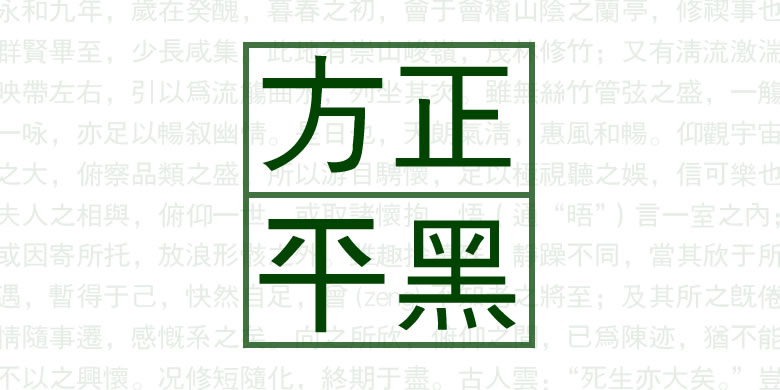
方正平黑
品牌:方正字库设计师:方正字模部发行时间:1996字库编码:大陆繁体(GB12345-90)、港台地区(BIG-5)分类:黑体
方正平黑
方正平黑是专门为港台地区用字设计的,只有繁体字库,一些笔形结构上与大陆标准有所不同。这款字体的笔画粗细适中,笔画两端无喇叭口,适用于报刊、书籍的正文排版。方正平黑有两种封装版本,其中BIG5编码是台湾制定的字库编码规范,包含两万多字,而GB12345-90编码的字数较少,约有七千字,是在简体字码位上放置了繁体字字形。繁简体往往不是一一对应,所以使用时需要注意校对。